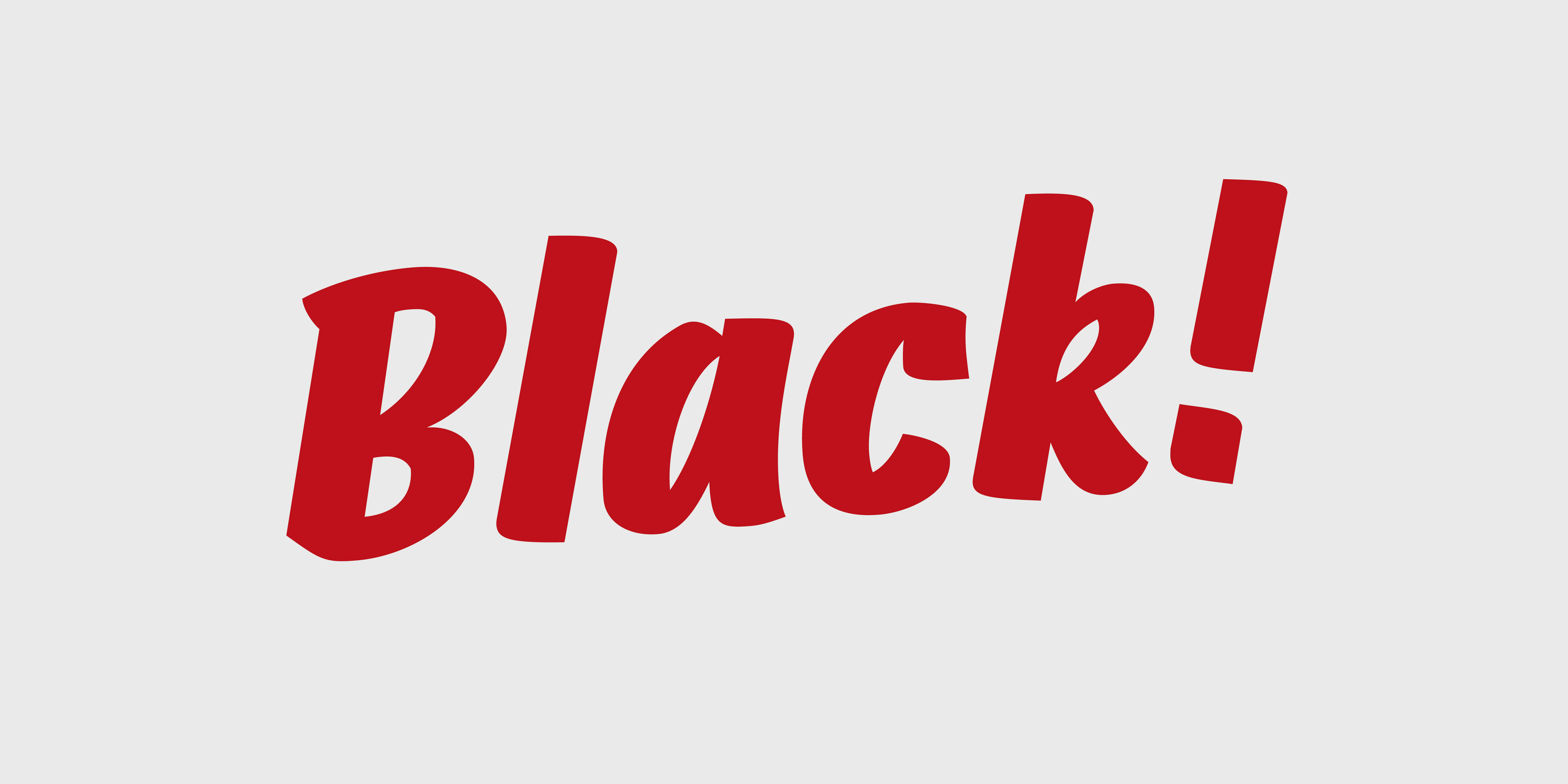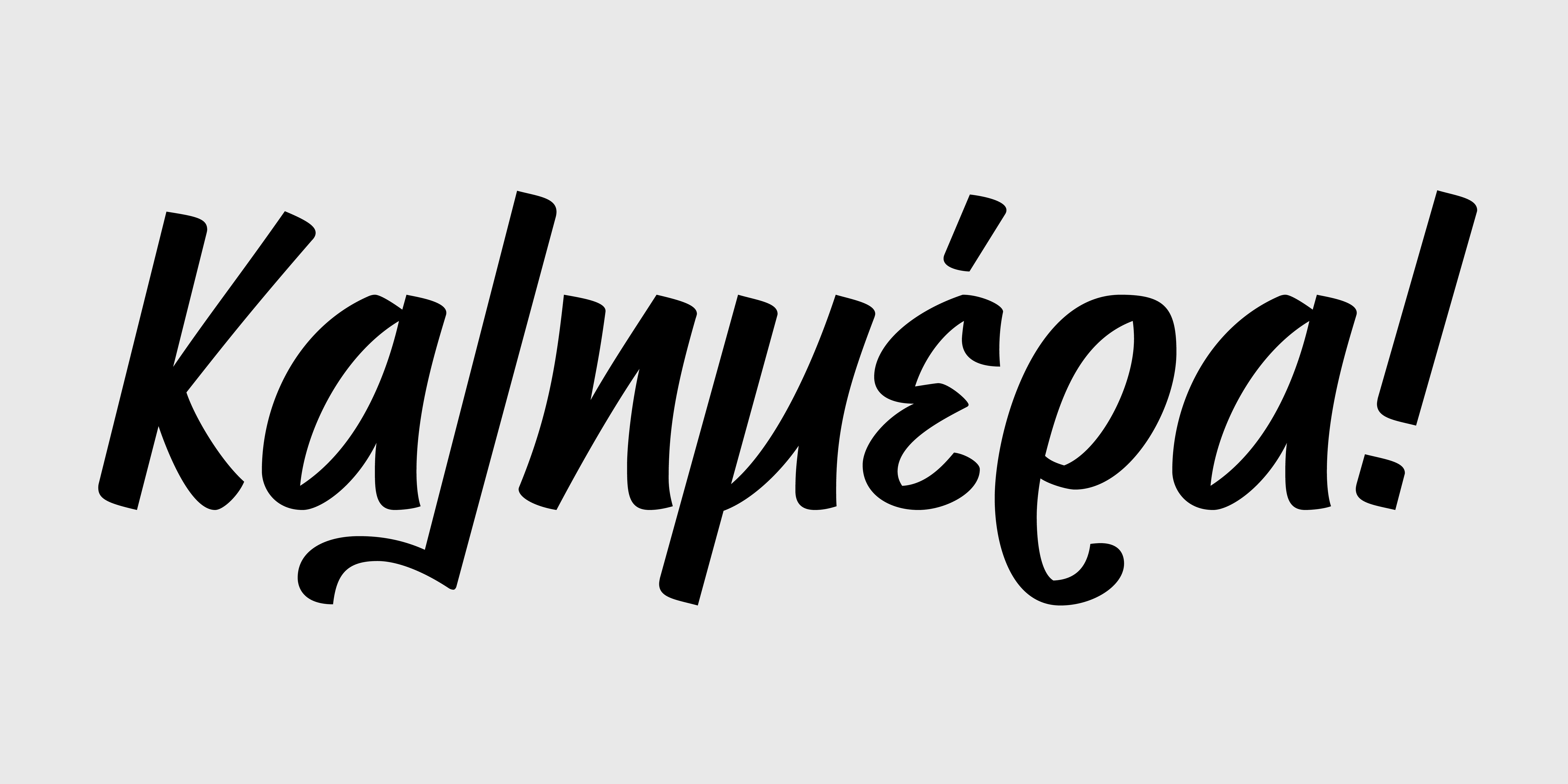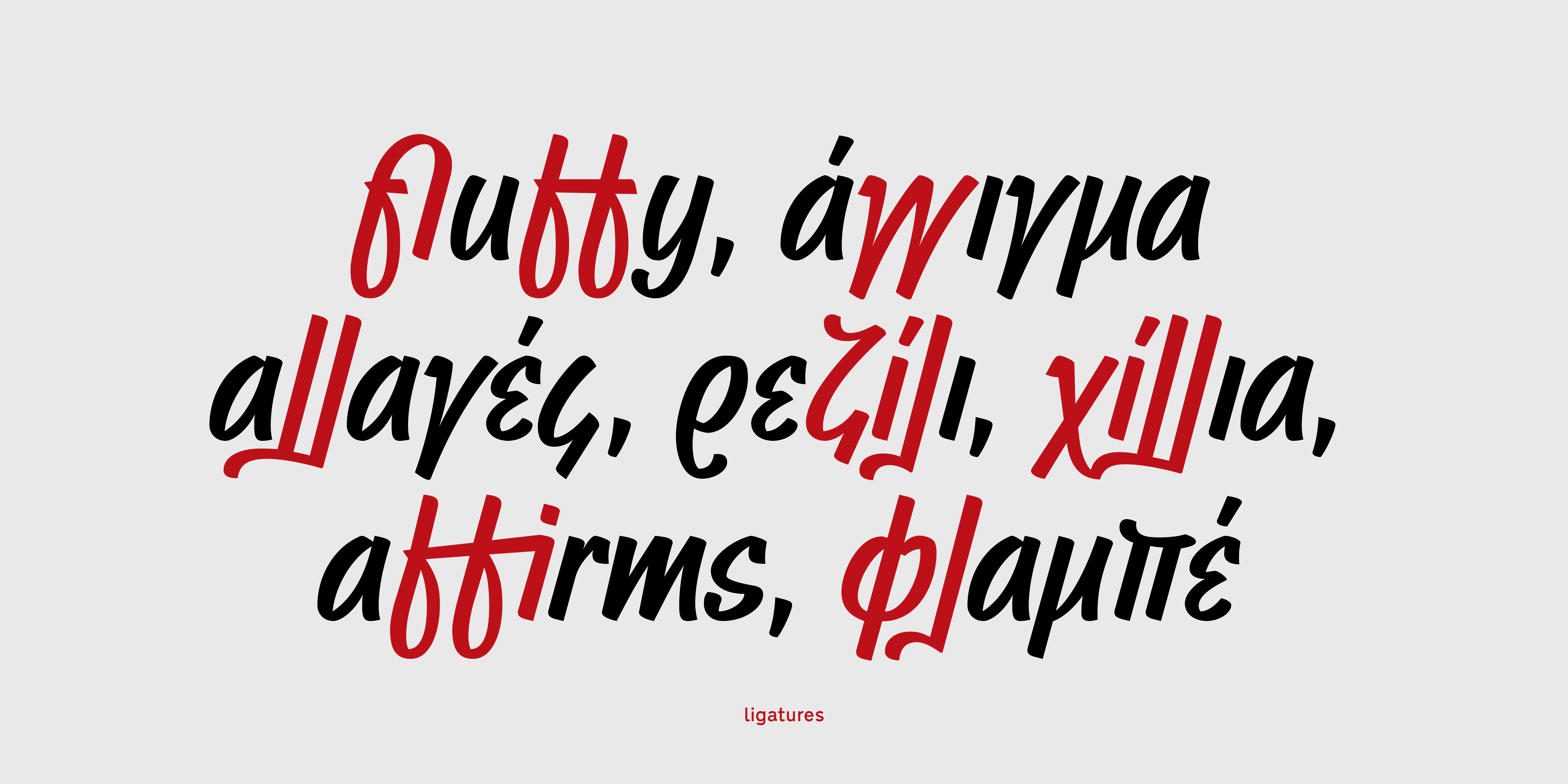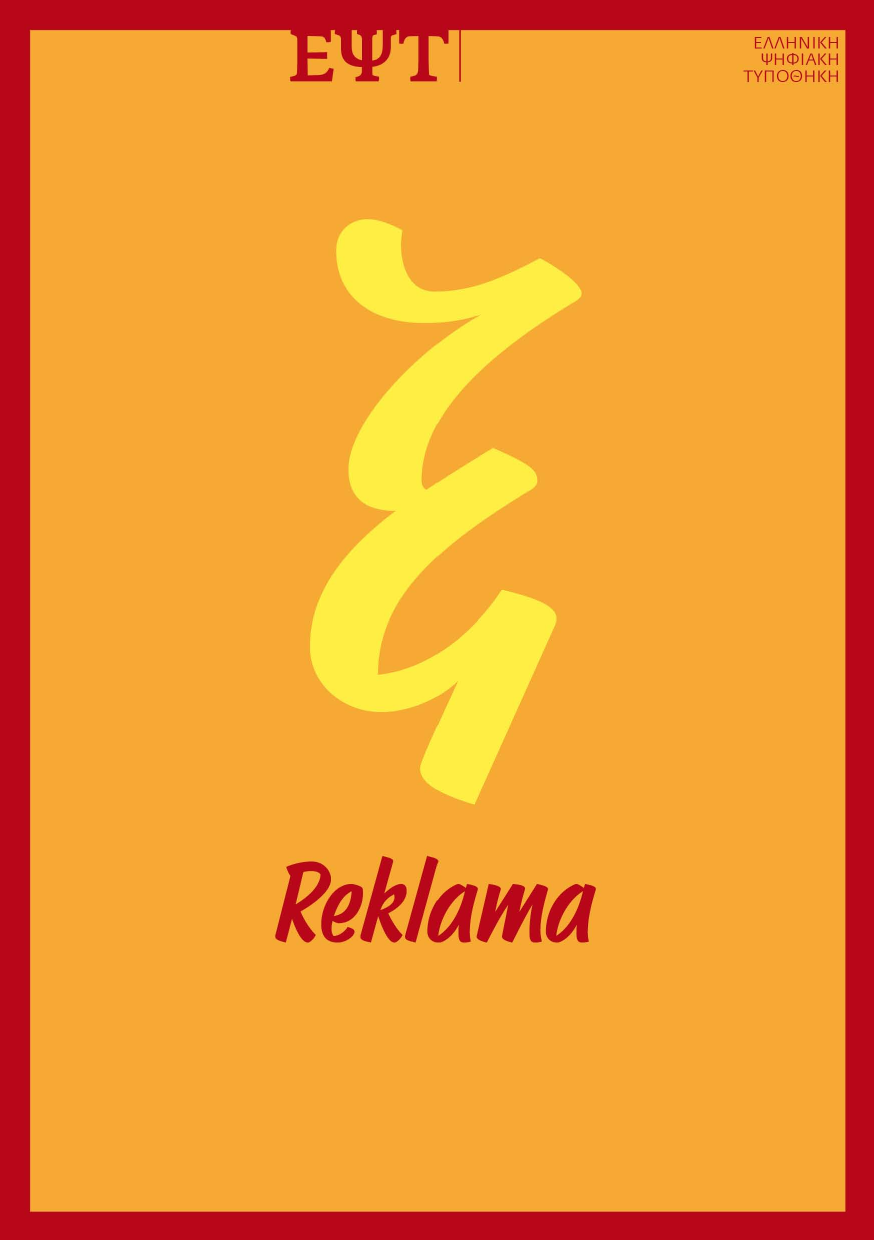
Reklama
Regular
Bold
Black
Η CF Reklama, η δεύτερη γραμματοσειρά του πρότζεκτ «Στέλλα», είναι μια προσπάθεια να μεταφράστει η νευρώδης γραφή του πλακέ μαρκαδόρου σε τυπογραφικά στοιχεία, διατηρώντας όμως την εκφραστικότητα του χειρόγραφου. Τα στοιχεία σχεδιάστηκαν ώστε να λειτουργούν ακόμη και σε μικρά μεγέθη, αλλά οι ιδιαίτερες φόρμες –όπως το «κοφτό» ταυ, ή το κατωφερές λάμδα– καθώς και διακριτικές λεπτομέρειες –όπως τα δακρύσχημα τελειώματα– αποκτούν μεγαλύτερο ενδιαφέρον σε μεγάλα μεγέθη. Η CF Reklama περιλαμβάνει τρία βάρη: κανονικά, έντονα και μαύρα, ώστε να είναι ευπροσάρμοστη σε κάθε ανάγκη τυπογραφικής επικοινωνίας, ανεξαρτήτως μεγέθους ή κλίμακας.